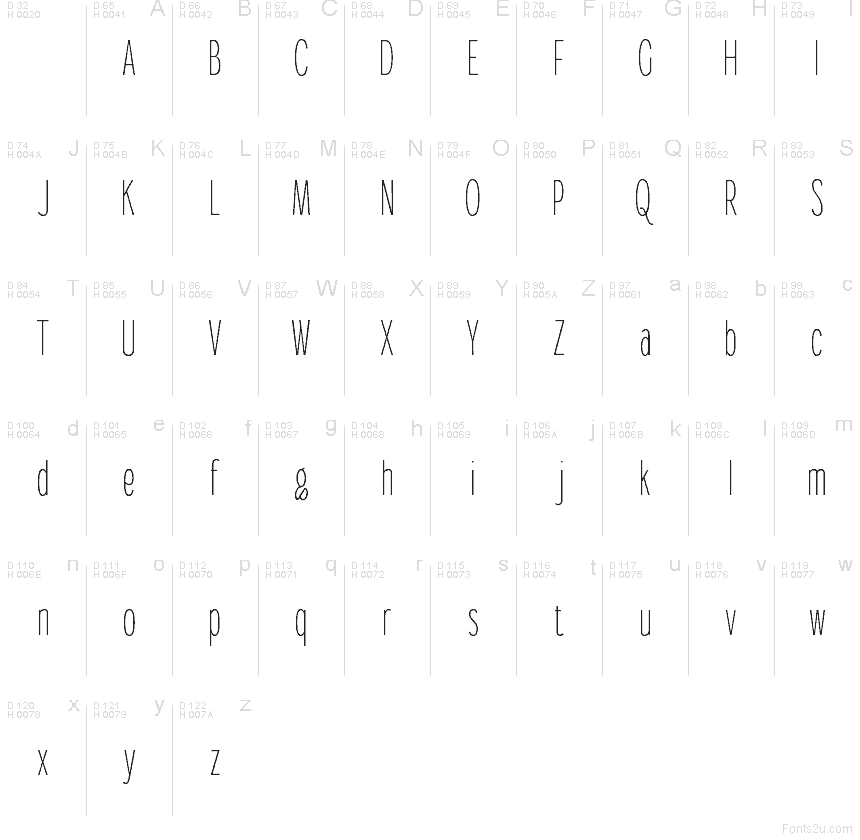
Miraelo Regular
Miraelo ist eine kostenlose serifenlose Schrift, die sich durch ihre sehr hohe, schmale Silhouette und lange vertikale Striche auszeichnet, die den Buchstaben einen sparsamen, aufrechten Rhythmus verleihen. Die abgerundeten Formen bleiben offen und schlicht im Kontrast zu den gestreckten Linien, wodurch das Design luftig und leicht formell wirkt, anstatt neutral zu sein.
Diese Form eignet sich hervorragend für Fashion-Branding, Parfümverpackungen, Boutiqueschilder, redaktionelle Überschriften und minimalistische Poster, bei denen die Höhe mehr Wirkung erzielt als das Gewicht. In kurzen Zeilen rahmen diese Schriftart Logos und Namensschilder perfekt ein, da ihre schlanken Proportionen für einen raffinierten vertikalen Rhythmus sorgen, anstatt einen dichten Textblock zu erzeugen.